35+ Font Google Terbaik untuk Blogging & Cara Memilih Font yang Ideal
Diterbitkan: 2024-07-12Saya mengambil 50 blog terpopuler di dunia dan memeriksa masing-masing blog satu per satu untuk melihat font apa yang digunakan. Setelah menyusun daftarnya, saya membuat sepuluh besar font yang paling banyak digunakan berdasarkan jumlah blog yang digunakan, baik di headline maupun di dalam teks artikel. 1
Font lainnya yang melengkapi daftar kami hanya digunakan sekali, tetapi wajar jika font tersebut layak disebutkan dalam postingan ini karena font tersebut adalah font yang paling diandalkan oleh blog paling populer di dunia saat ini.
Sekarang setelah Anda memahami konteks yang membuat saya memilih font untuk daftar ini, mari beralih ke daftar itu sendiri. Namun sebelum itu, berikut sekilas tabel yang menampilkan sepuluh font terpopuler:
| huruf | # blog yang menggunakannya | Blog |
|---|---|---|
| Piagam | 6 | Elle, Cosmopolitan, Esquire, Harper's Bazzar, Mata-Mata Digital, Kesehatan Pria |
| robot | 5 | Mencari Alpha, Gizmodo, Berita Olahraga, FanSided, Loudwire |
| Buka San | 4 | Lebih keras, Cointelegraph, E! Berita, Ars Technica, |
| Antar | 4 | Pengusaha, EssentiallySports, theScore.com, Majalah Far Out, |
| Montserrat | 4 | talkSPORT, HipHopDX, Mata-Mata Digital, FanSided |
| Helvetica | 3 | Papan iklan, NME, TechCrunch |
| Georgia | 3 | RollingStone, Gizmodo, Mashable |
| waktu | 3 | Business Insider, Tinjauan Bisnis Harvard, Pitchfork |
| Arial | 2 | Halaman Enam, Tren Bisnis Kecil |
| Poppin | 2 | HotNewHipHop, 90 menit |
🔥 Font terbaik untuk blogging (oleh Google Font dan sumber lainnya)
Ringkasan singkat tentang temuan saya:
- Charter – font yang paling banyak digunakan di 50 blog teratas di dunia
- Roboto – Font Google yang paling banyak diunduh dan paling banyak digunakan kedua di blog populer
- Open Sans – font Google yang paling banyak diunduh kedua dan paling banyak digunakan ketiga di blog populer
Masing-masing font yang muncul dalam penelitian saya, satu per satu:
1. Piagam
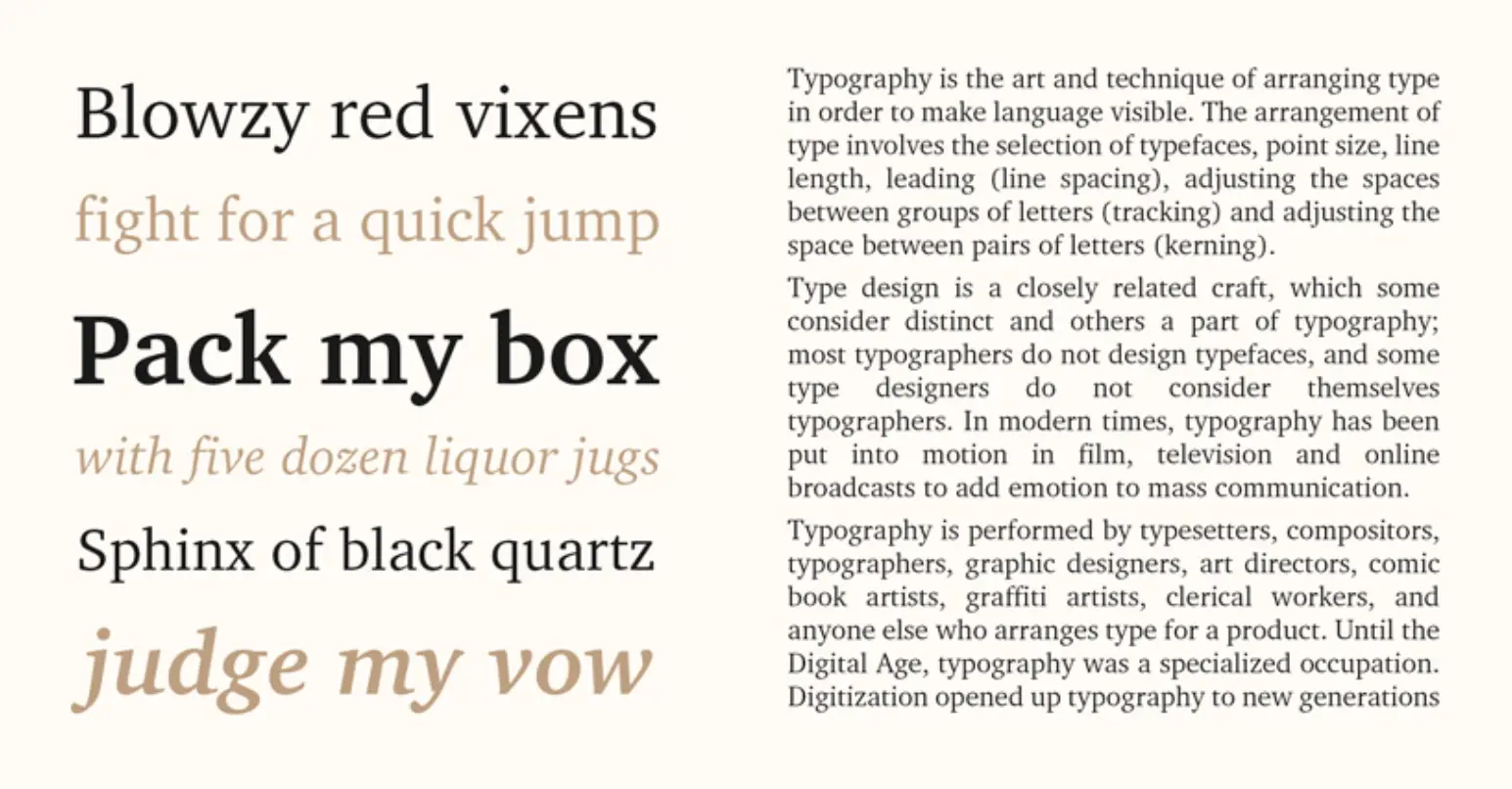
Charter menempati posisi pertama karena paling banyak digunakan di seluruh blog teratas yang kami analisis. Font ini bukan bagian dari keluarga Google, tetapi Anda akan melihatnya di banyak blog di seluruh dunia, apa pun niche-nya.
2. Robot
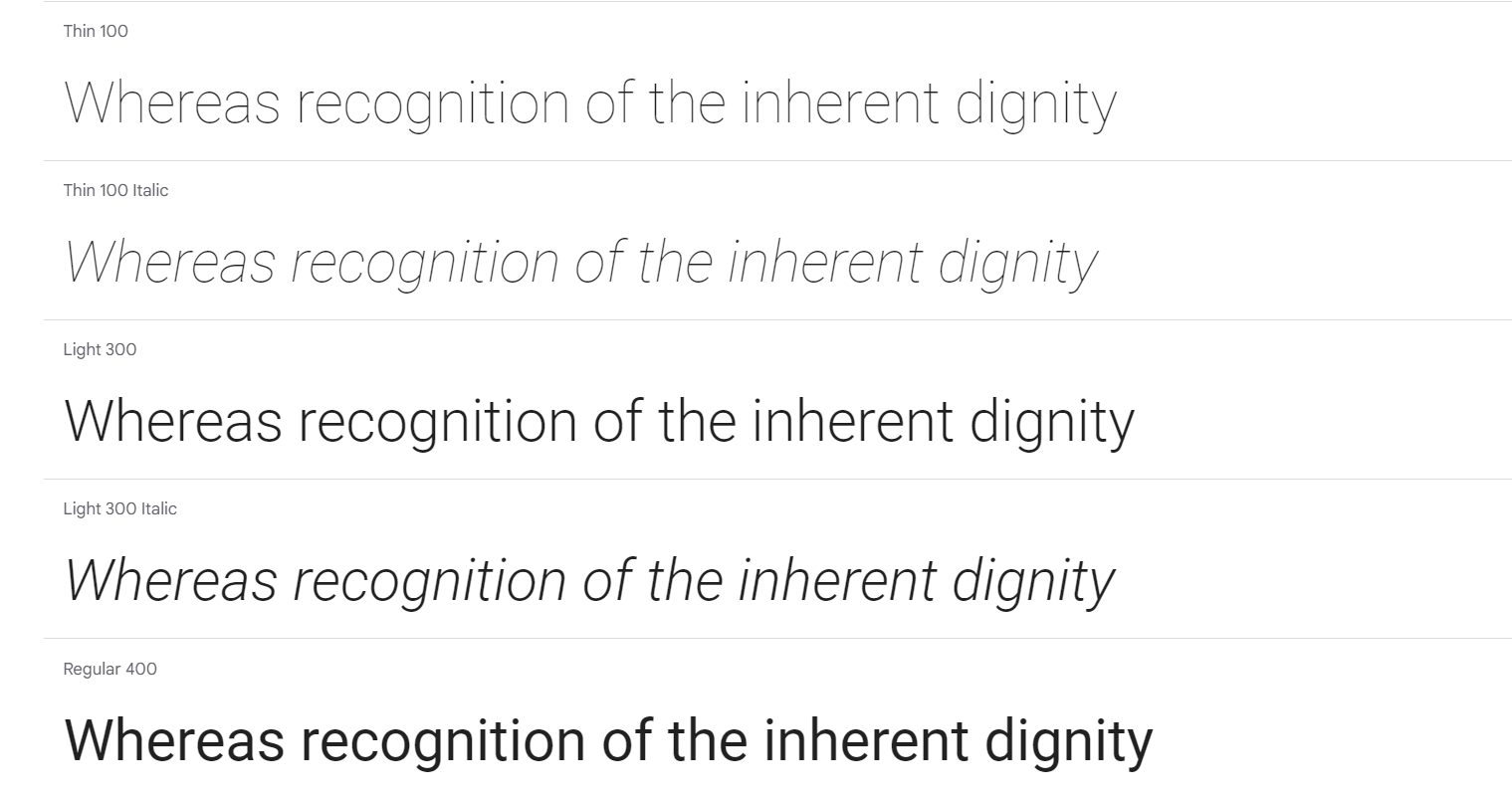
Roboto sejauh ini merupakan Google Font yang paling banyak diunduh dan dipasang, seperti yang ditunjukkan oleh statistik. Alasannya adalah karena desainnya geometris namun ramah. Ini menciptakan lingkungan membaca yang alami dan lancar serta memberikan profesionalisme yang dibutuhkan sebagian besar penulis.
3. Buka Sans
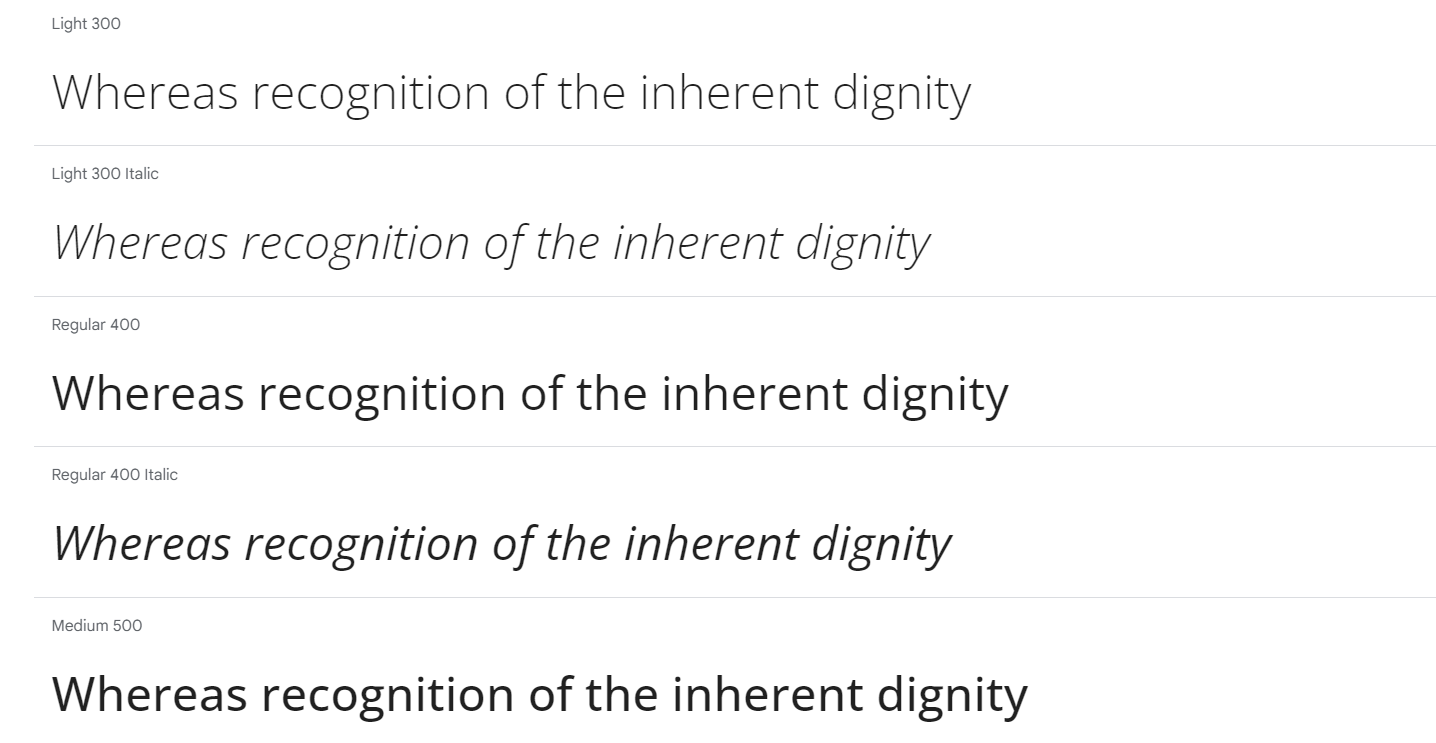
Open Sans berfokus pada netralitas dan keramahan, memungkinkan penggunaannya dalam hampir semua format, mulai dari media cetak hingga publikasi internet. Faktanya, Open Sans adalah font kedua yang paling banyak diunduh di Google.
4. Antar
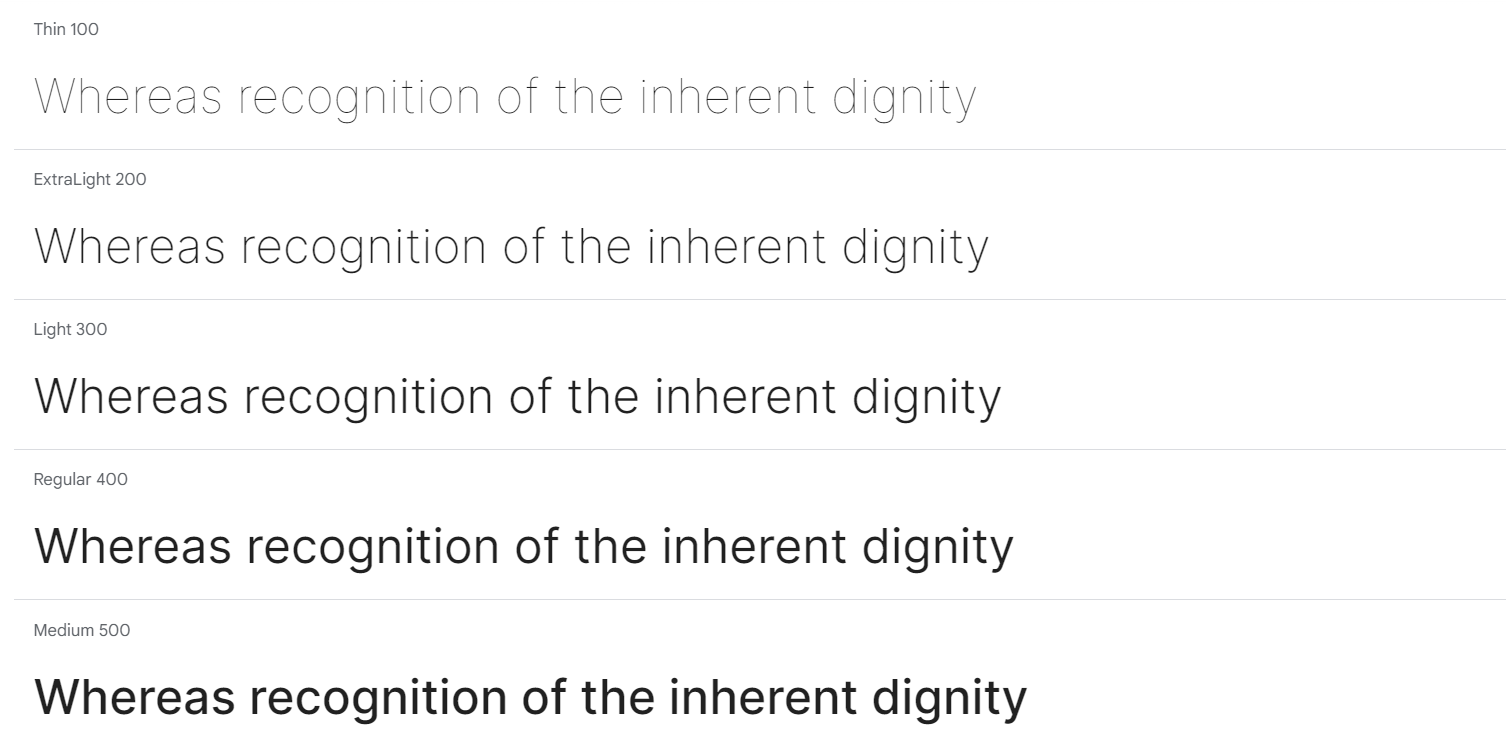
Meskipun mungkin tidak termasuk dalam sepuluh font teratas Google, Inter berhasil masuk ke dalam lima font teratas kami dan tampaknya cocok untuk blogging.
5. Montserrat
Font Google populer lainnya yang juga disukai oleh blog terkenal di seluruh dunia.
6. Helvetica
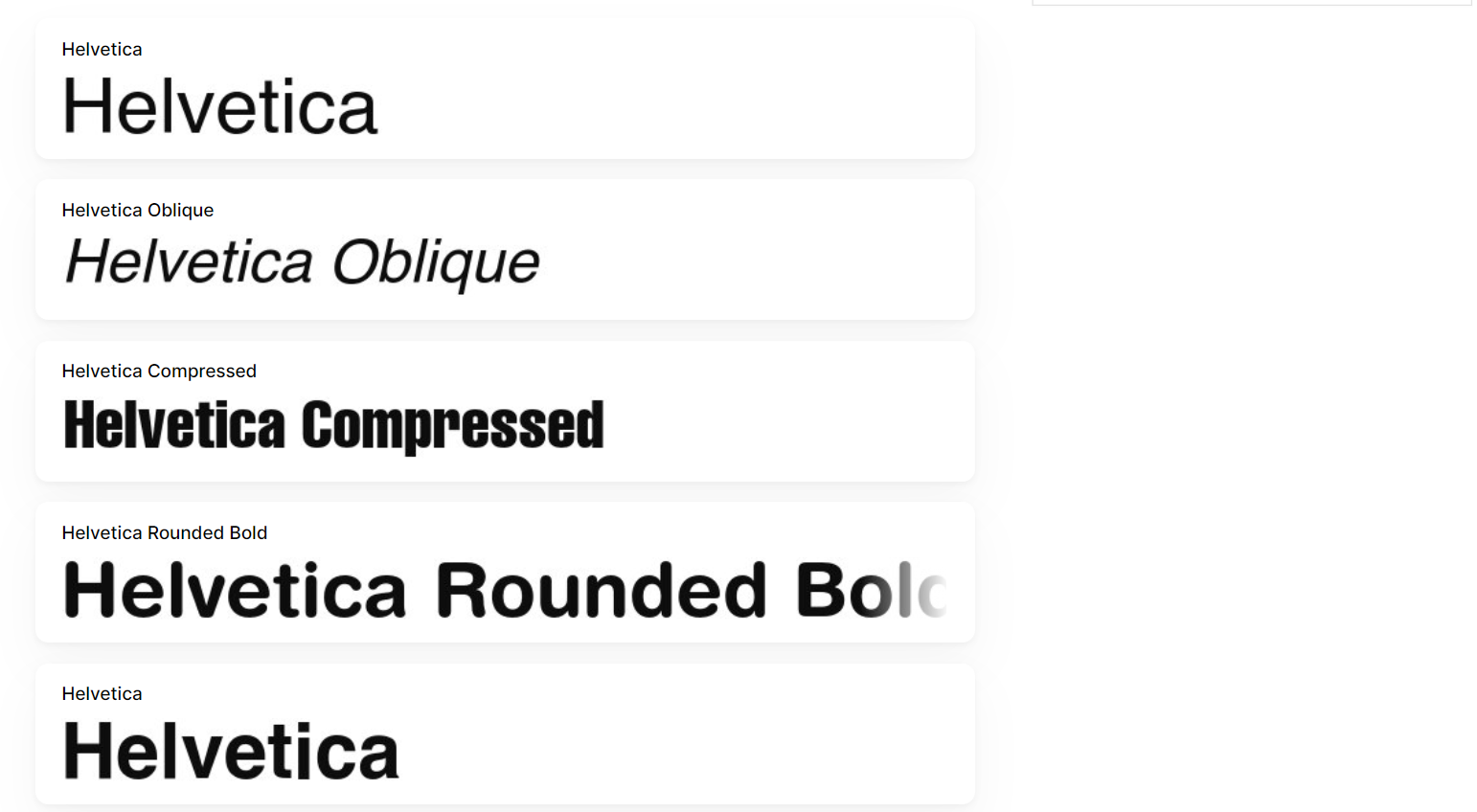
Helvetica adalah salah satu tipografi paling terkenal di dunia dan fakta bahwa tipografi ini ada dalam daftar ini bukanlah suatu kejutan. Nama aslinya adalah Neue Haas Grotesk, yang menurut saya digunakan di beberapa headline blog, khususnya dengan nama ini.
7.Georgia
Georgia adalah font serif yang awalnya dirancang untuk Microsoft tetapi kemudian diperluas ke World Wide Web dan, secara implisit, mulai digunakan di beberapa blog yang paling banyak dikunjungi saat ini.
8. Waktu
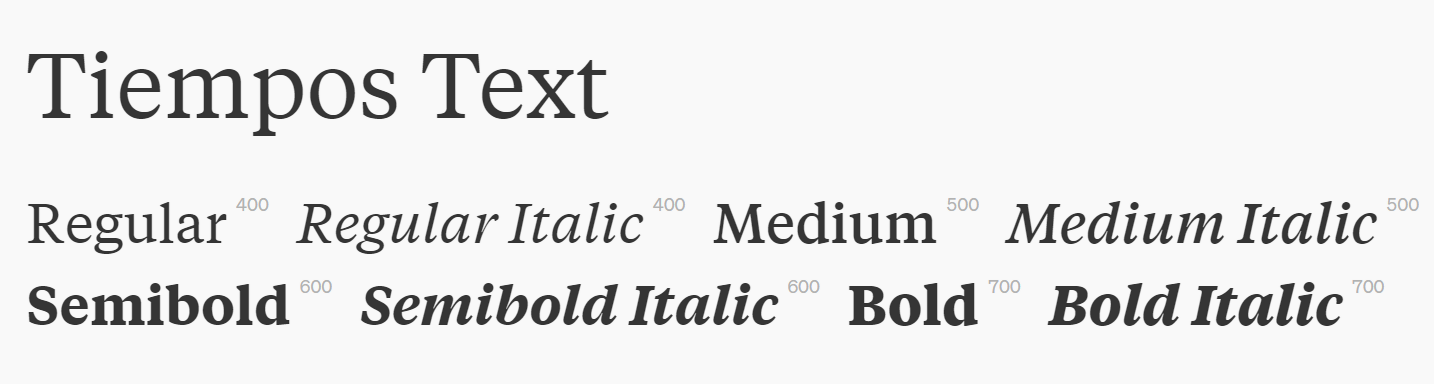
Tiempos adalah jenis huruf yang hadir dengan sentuhan modern dan sangat cocok untuk majalah atau blog yang membutuhkan tampilan lebih mewah daripada klasik.
9. Arial
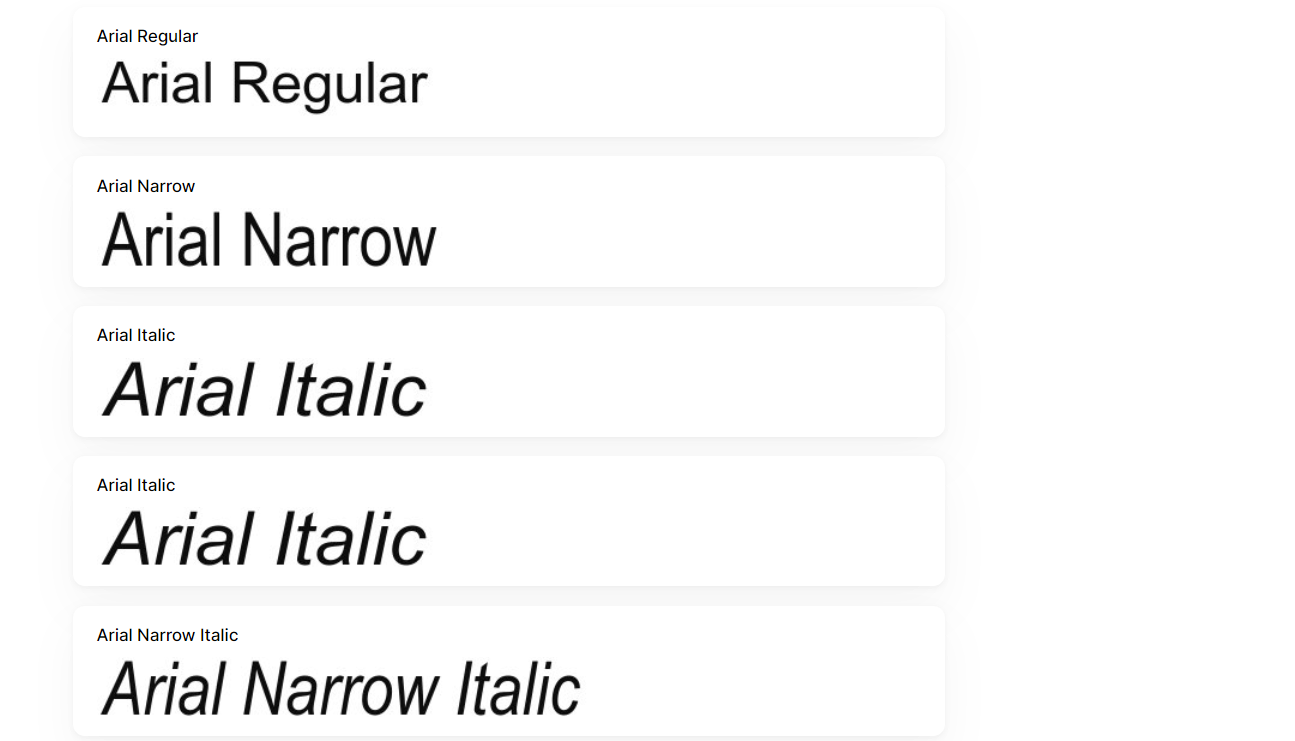
Arial adalah font sans-serif yang menghadirkan netralitas. Desain yang netral dan teratur ini menjadikannya pilihan yang aman untuk hampir semua jenis blog. Ini adalah salah satu tipografi default Windows.
10. Poppin
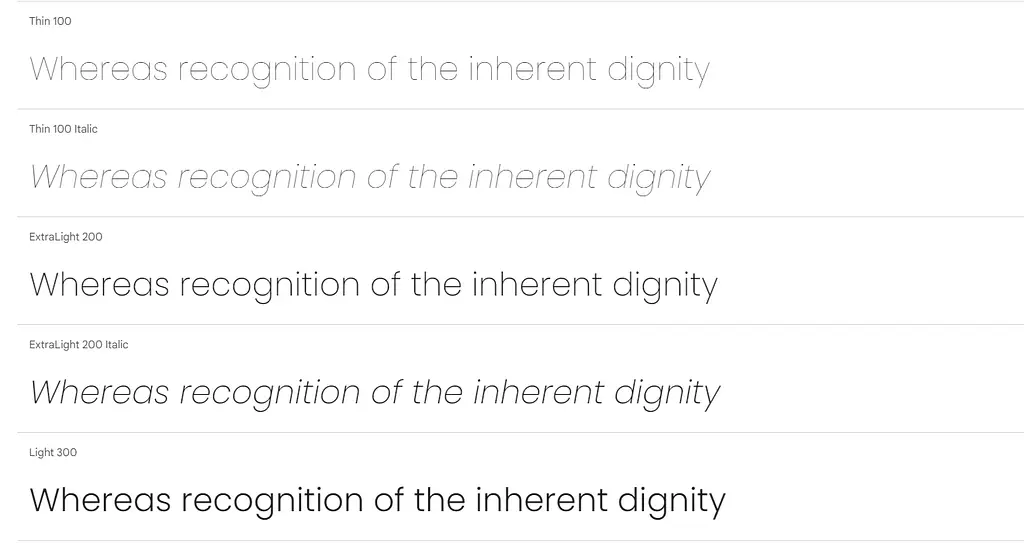
Salah satu favorit orang dari perpustakaan Google, Poppins memiliki desain yang berbeda karena jarak antar karakter yang lebar.
Lebih banyak font blog untuk inspirasi Anda
Itu tadi sepuluh besar font yang paling sering muncul di blog populer. Namun, karena saya telah menelusuri total 50 blog, sayang sekali jika tidak menyebutkan font lain yang saya temukan di situs tersebut. Jadi, jika Anda belum yakin untuk menggunakan salah satu font yang saya tampilkan sejauh ini, lihat daftar ini:
- Pantun jenaka
- Lato
- Sumber Sans Pro
- LabAneh
- Muli
- Lora
- Poli
- Tampilan Saol
- Proksima Nova
- Garamond Perdana Menteri
- Buku Sekuel Sans
- Teks Breve
- Teks Langit
- Didaktik Gotik
- Monumen Grotesk
- Judul Publiko Tebal